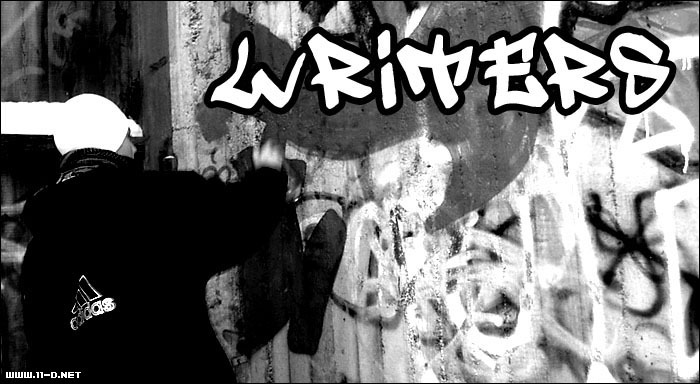
Writers Original, di Johan Waldenstrom, è un font graffiti gratuito che cattura la rapidità e l'energia di un tag fatto con il pennarello. Le lettere puntano su angoli vivi e tratti decisi, con uno stile a mano libera che sembra improvvisato anziché rifinito, conferendo all'intero font una vibrante energia di strada.
È perfetto per skatezine, copertine di mixtape, titoli di poster, flyer per club e cartelli dove conta più un aspetto grezzo e scritto a mano che la precisione. Essendo un font gratuito, è particolarmente adatto per parole brevi, nomi di artisti e richiami grafici, poiché il ritmo irregolare e la spaziatura asimmetrica creano un forte impatto visivo.